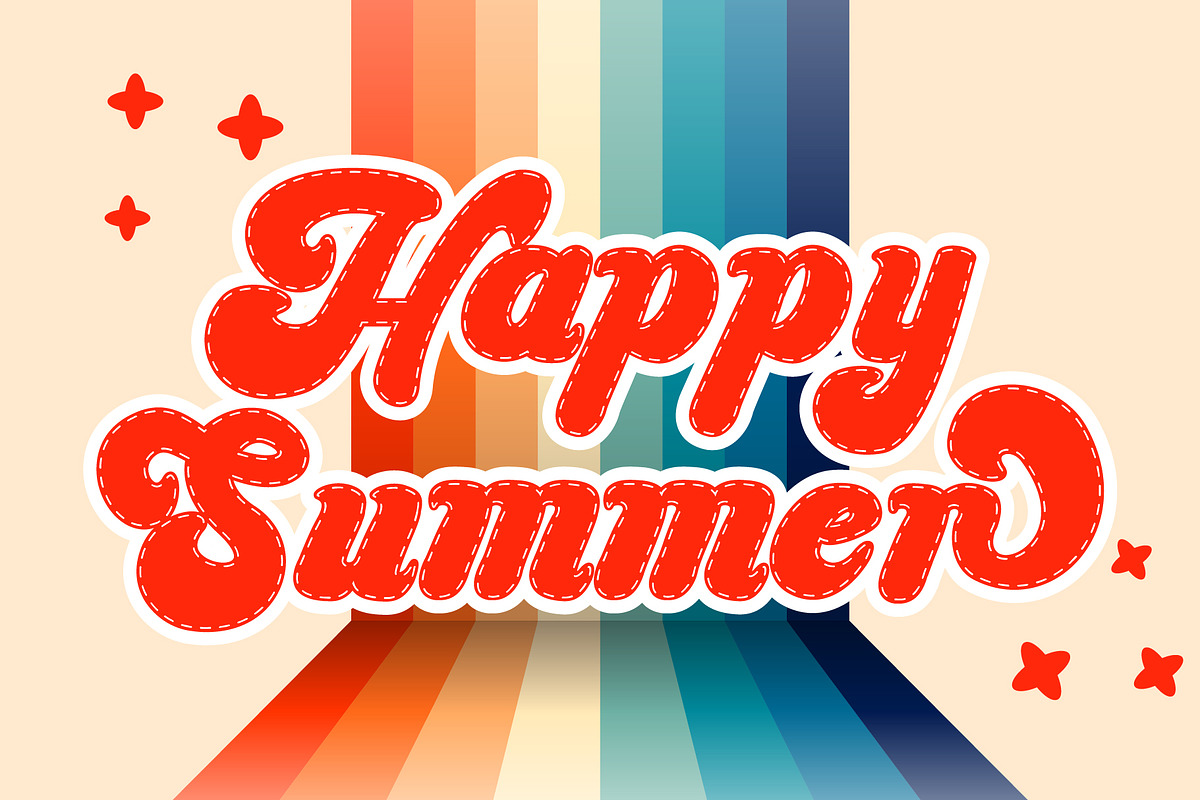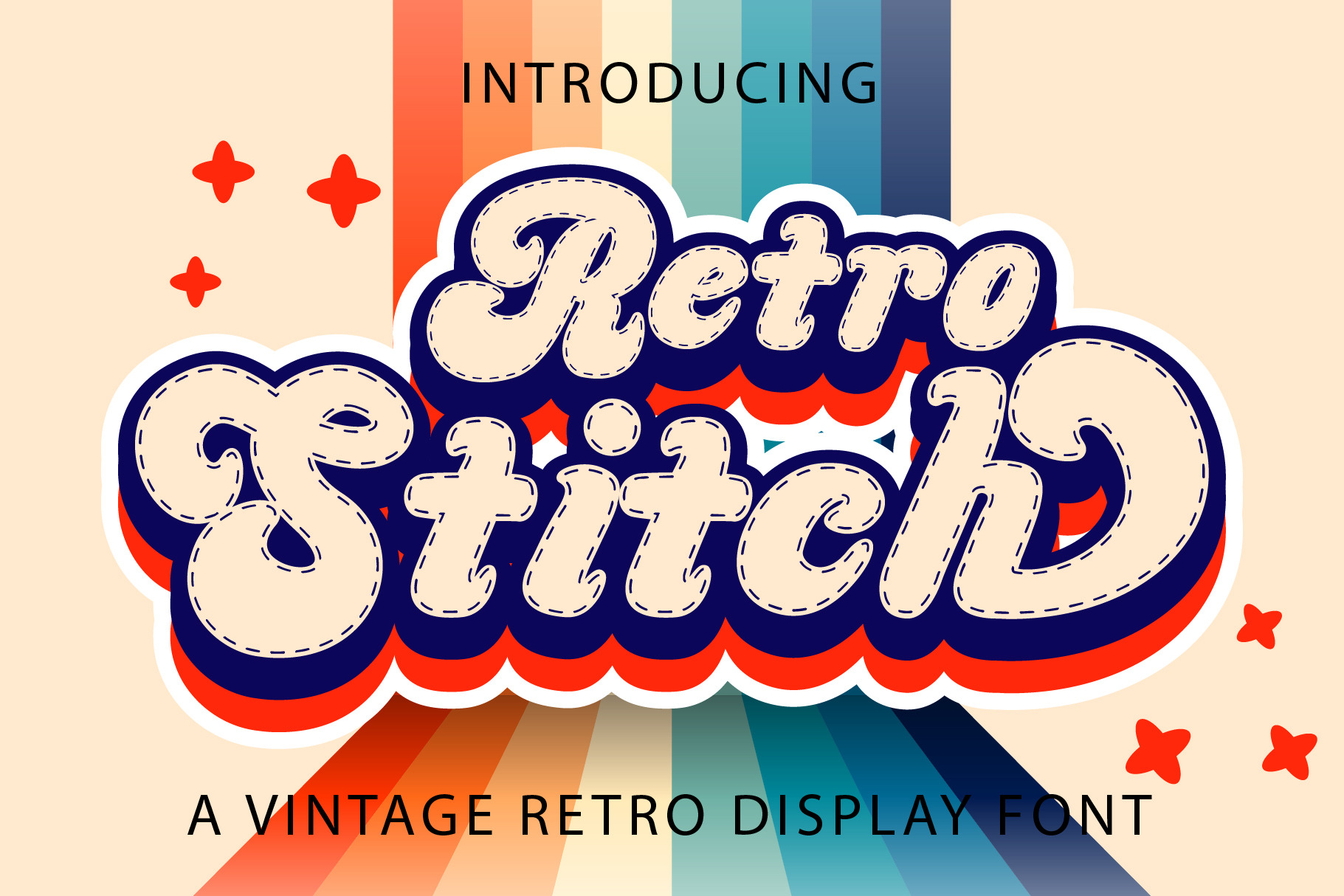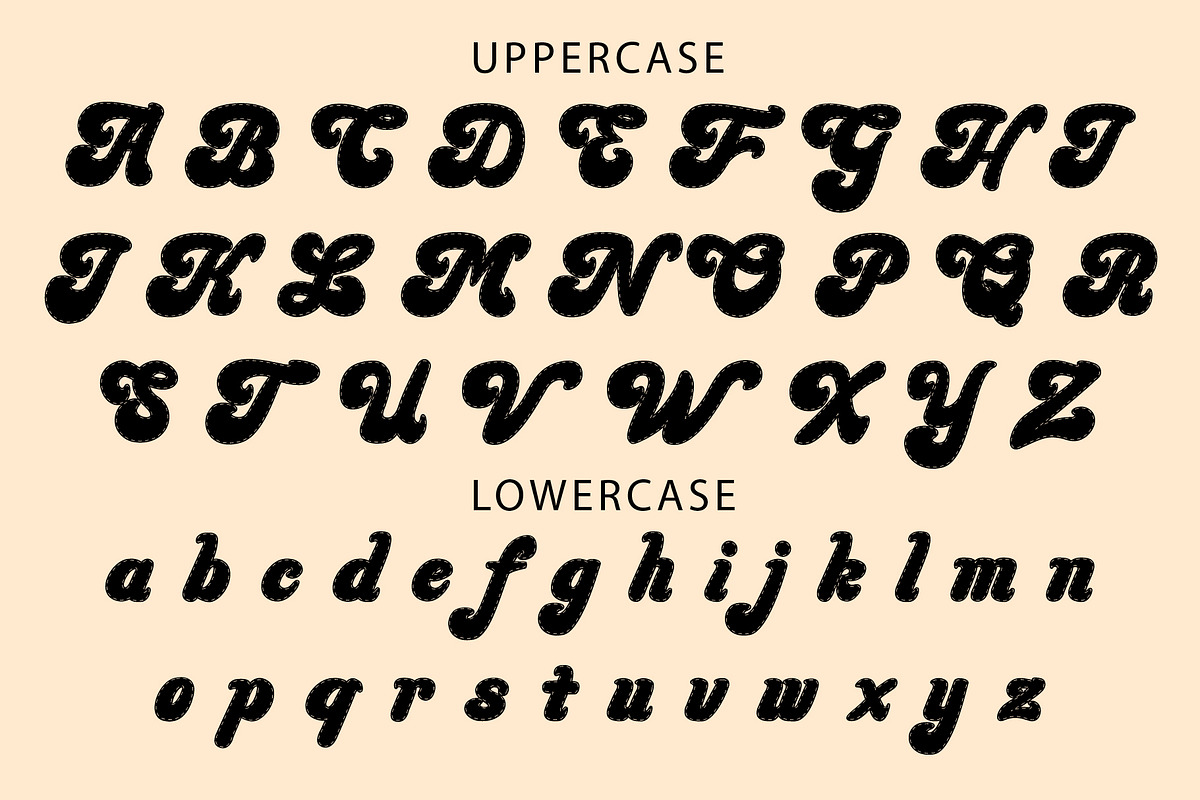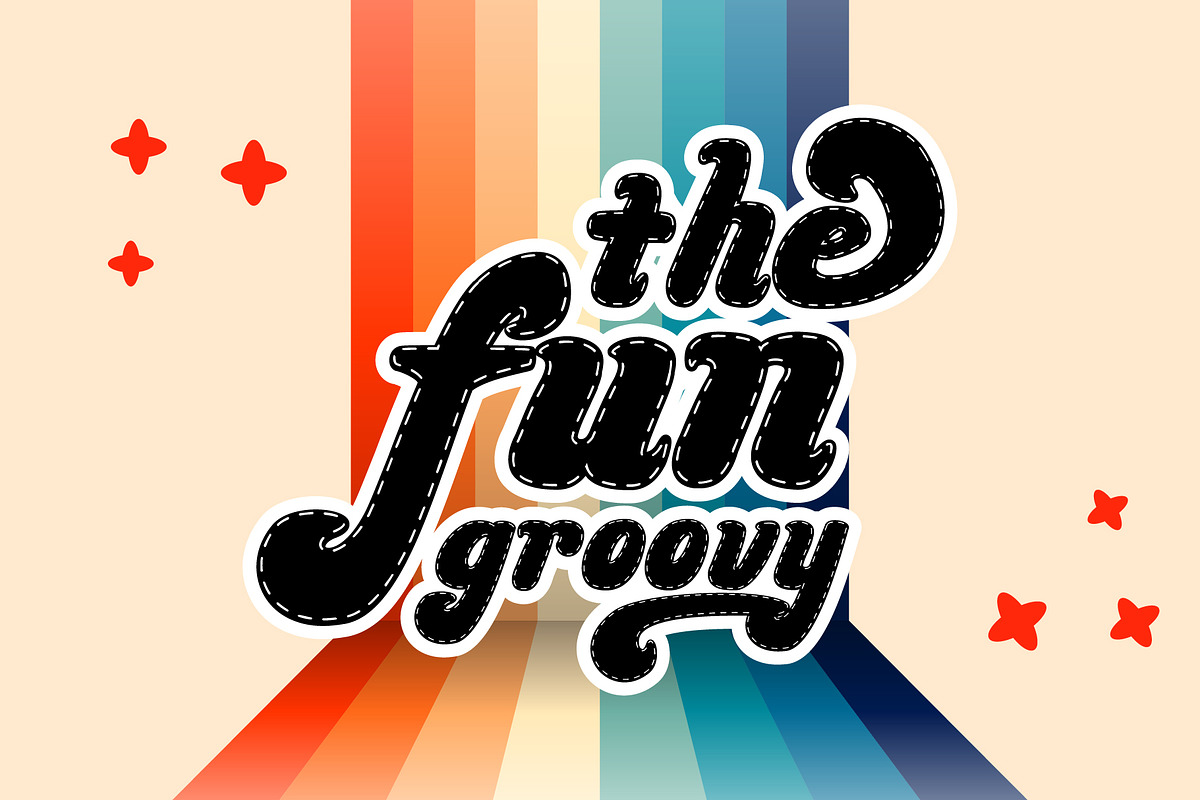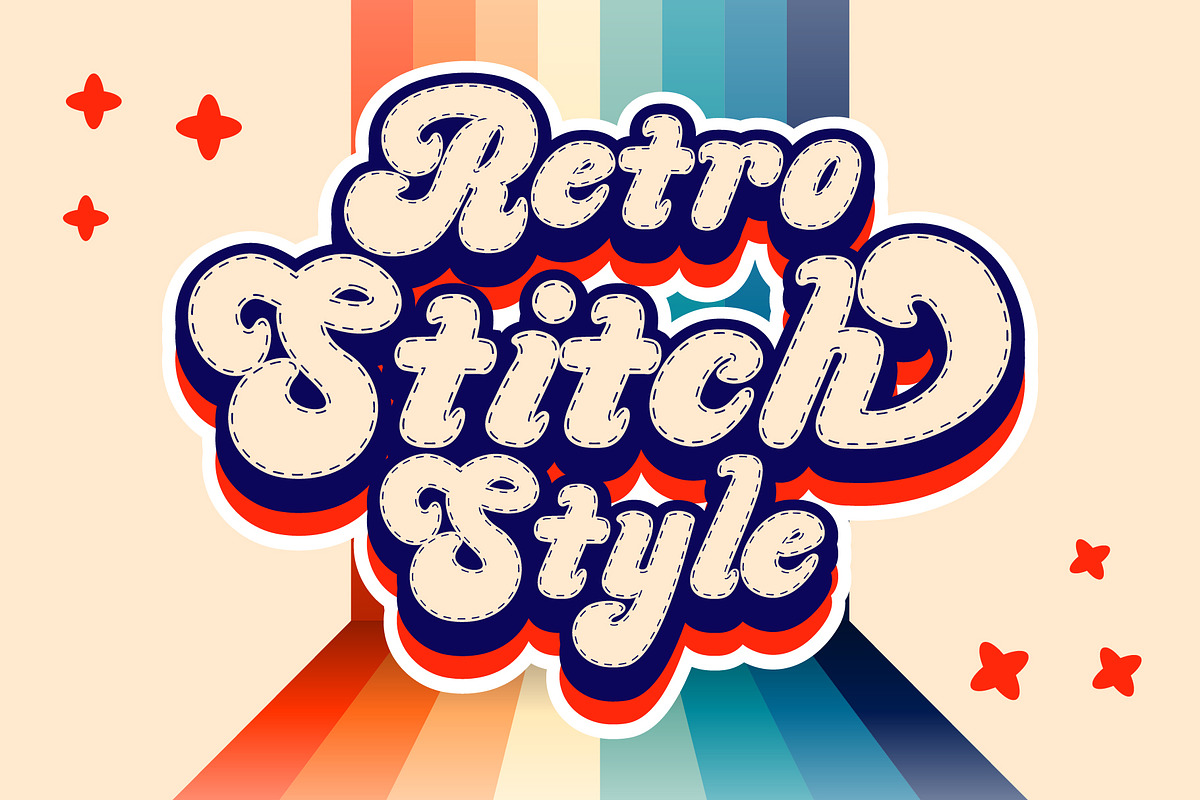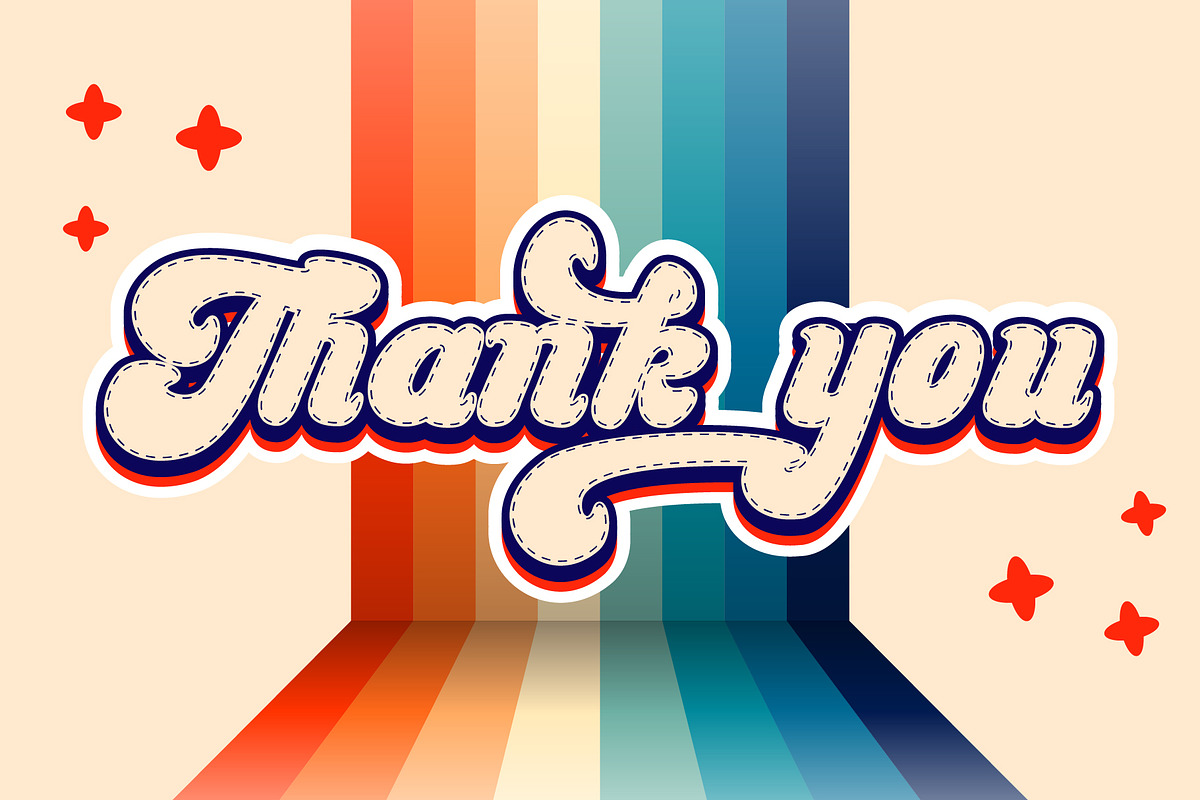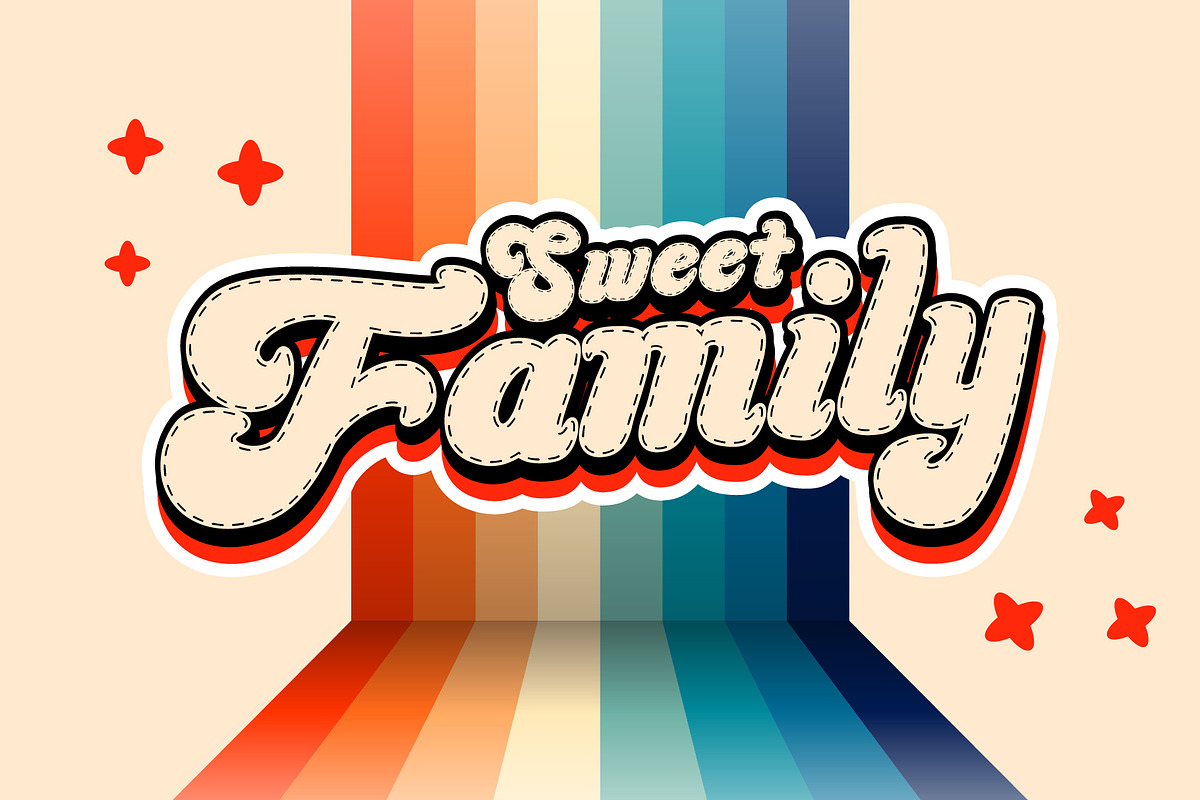
Retro Stitch - Retro Font
Retro Stitch adalah font tampilan bergaya vintage yang keren. Gunakan untuk menambahkan sentuhan retro khusus pada ide desain apa pun! Font ini dapat digunakan untuk logo, branding, undangan, alat tulis, desain pernikahan, posting media sosial, dan banyak lagi! Font ini dikodekan PUA yang berarti Anda dapat mengakses semua glyph dan swash dengan mudah!